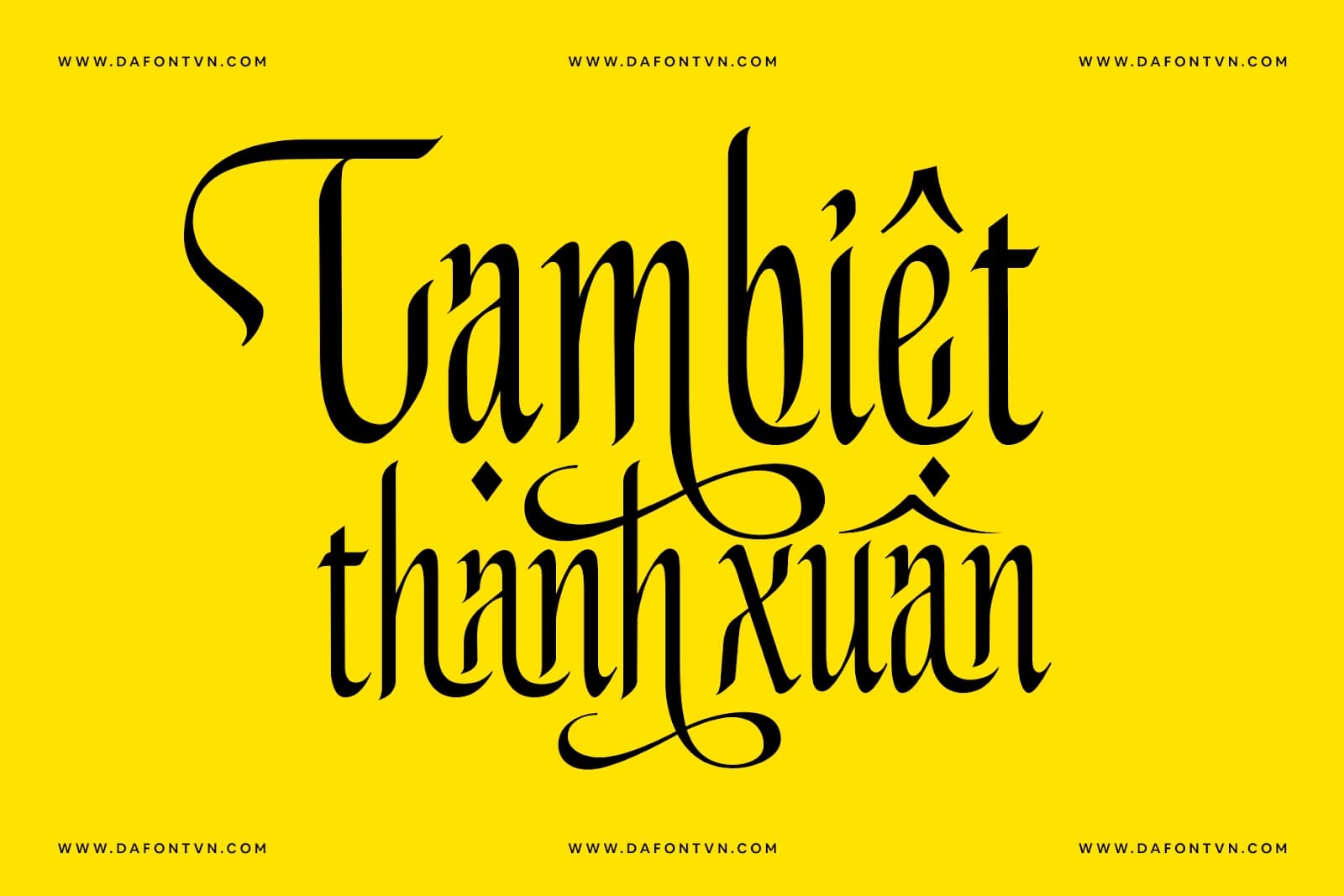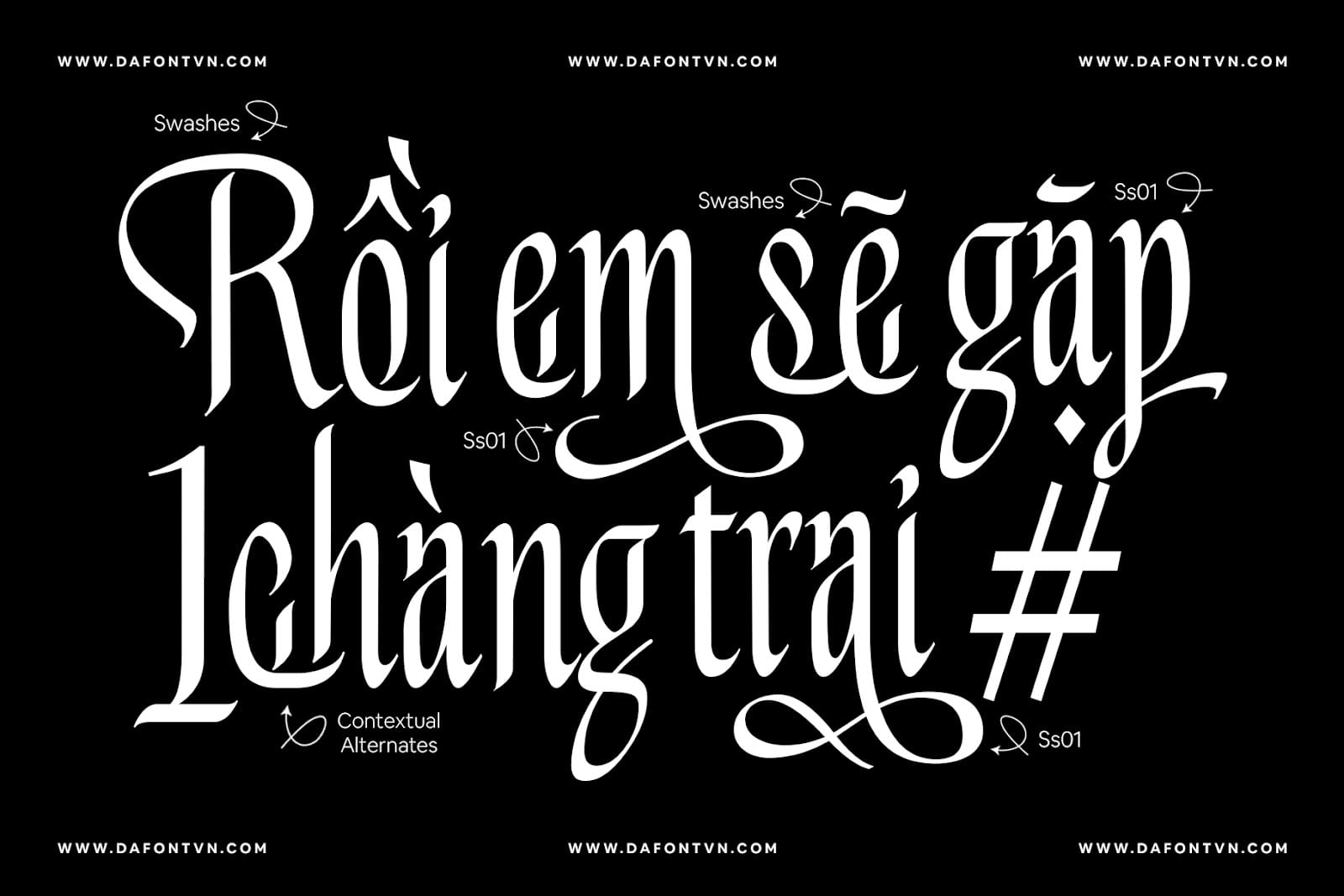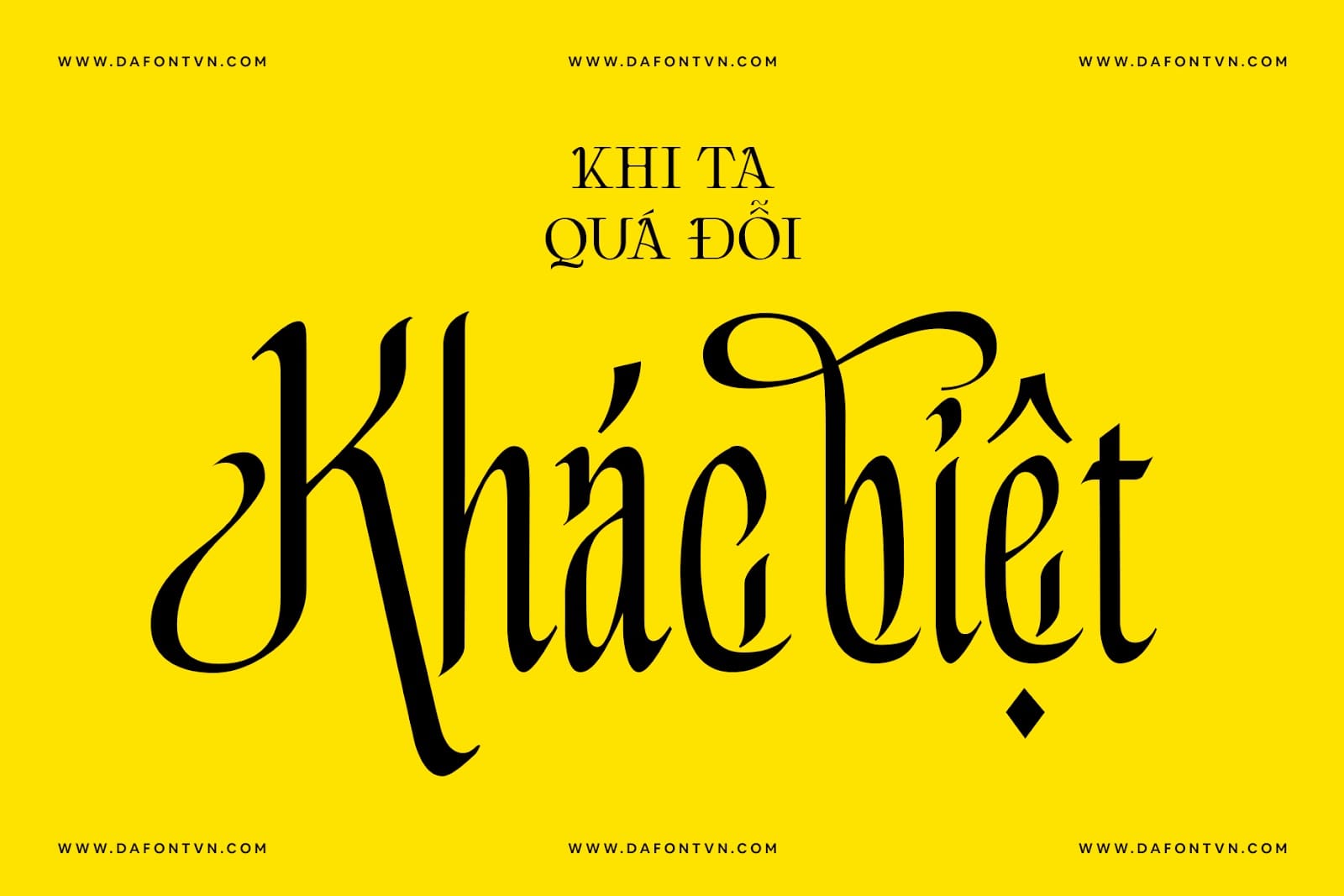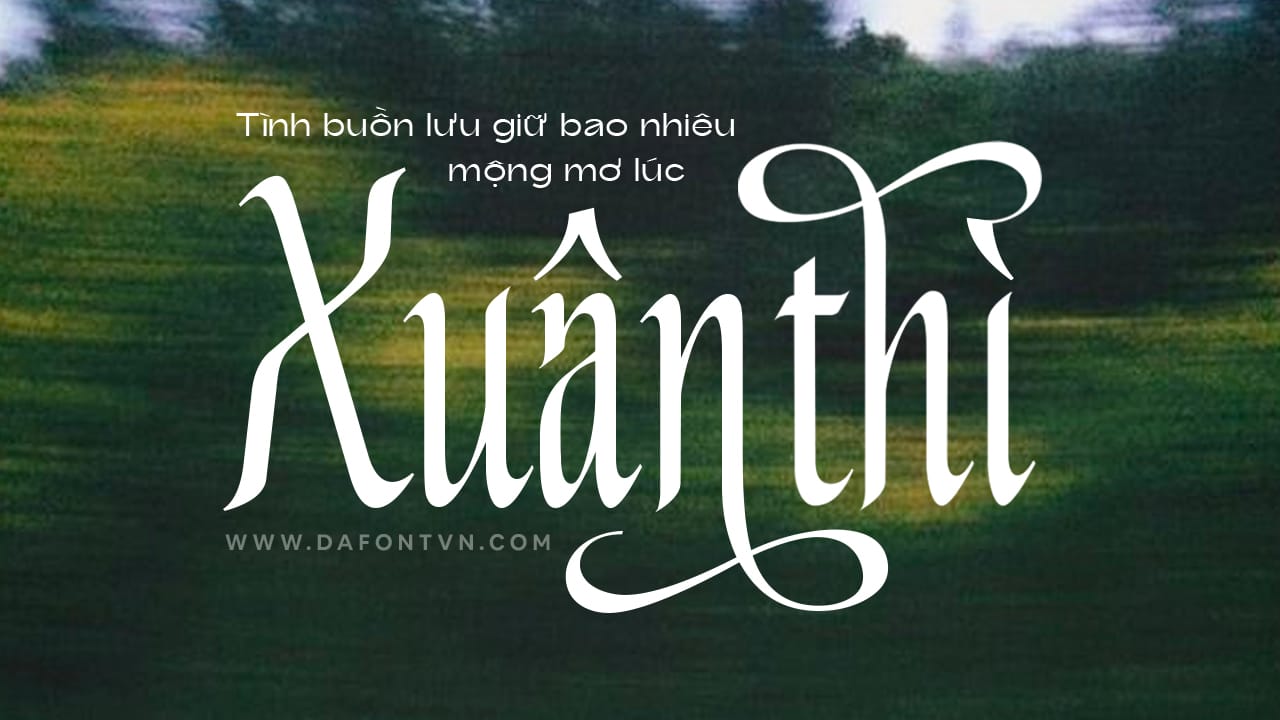
Lotape là kiểu chữ viết tay lấy cảm hứng từ các chữ cái thư pháp mang đến một phong cách mới mẻ và hiện đại. Nó được thiết kế nổi bật với cấu trúc ligature structure ấn tượng. Ngoài ra, nó còn độc đáo hơn với các lựa chọn thay thế chữ ghép phong phú giúp bạn tạo ra các tác phẩm thiết kế mới mẻ và đẹp mắt.
Lotape font phù hợp cho rất nhiều thiết kế khác nhau đặc biệt sử dụng làm tiêu đề nó sẽ làm nổi bật kiểu chữ khi sử dụng ở kích thước lớn, mặc dù nó vẫn hiển thị tốt ở kích thước nhỏ. Font chữ phù hợp cho thiết kế poster, bao bì, bìa truyện, thiệp mời…
Đặc biệt font còn hỗ trợ tính năng OpenType giúp bạn tha hồ kết hợp các ký tự thay thế để tạo ra cho mình những tác phẩm ấn tượng hơn.